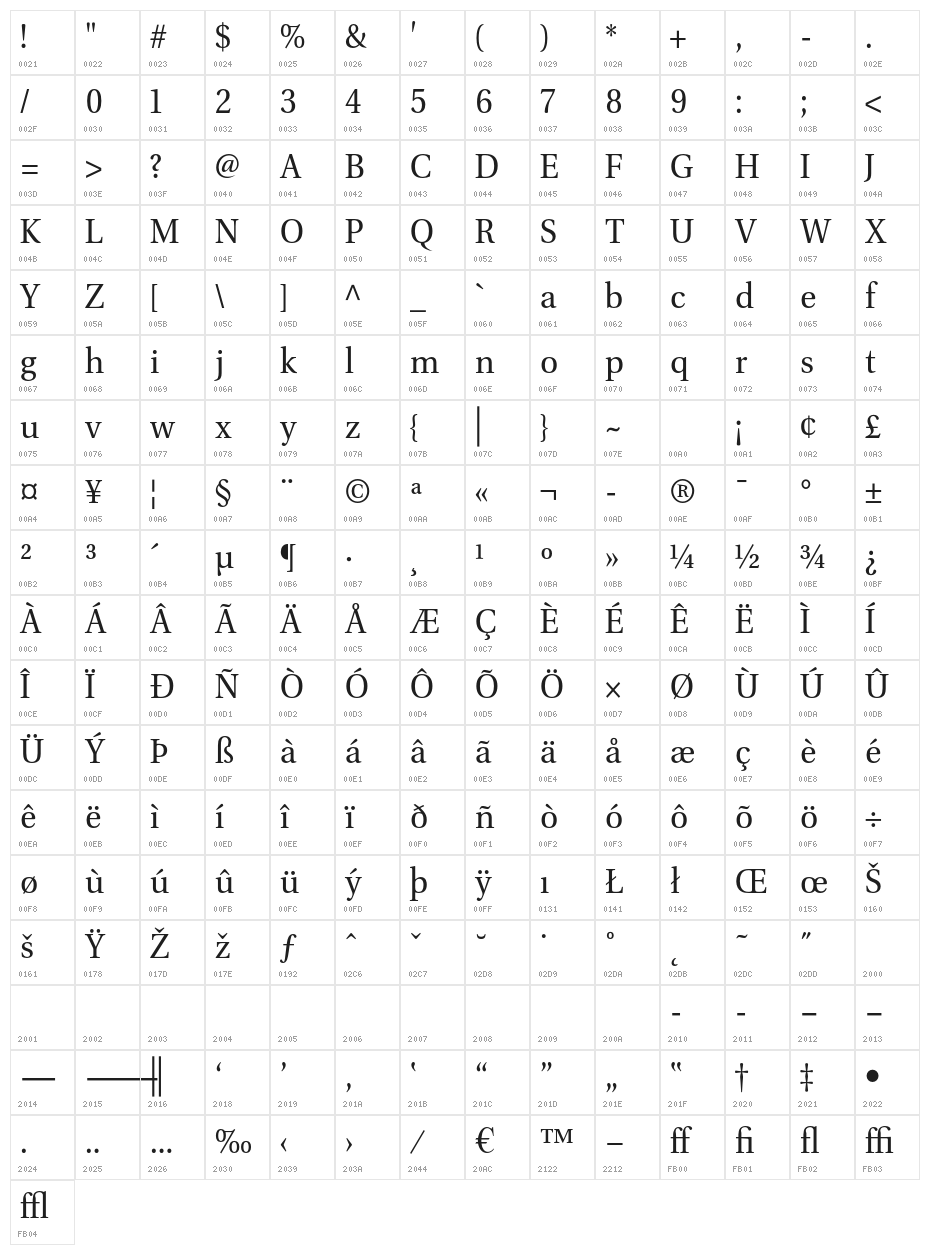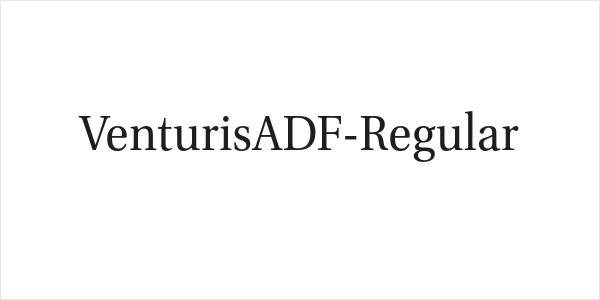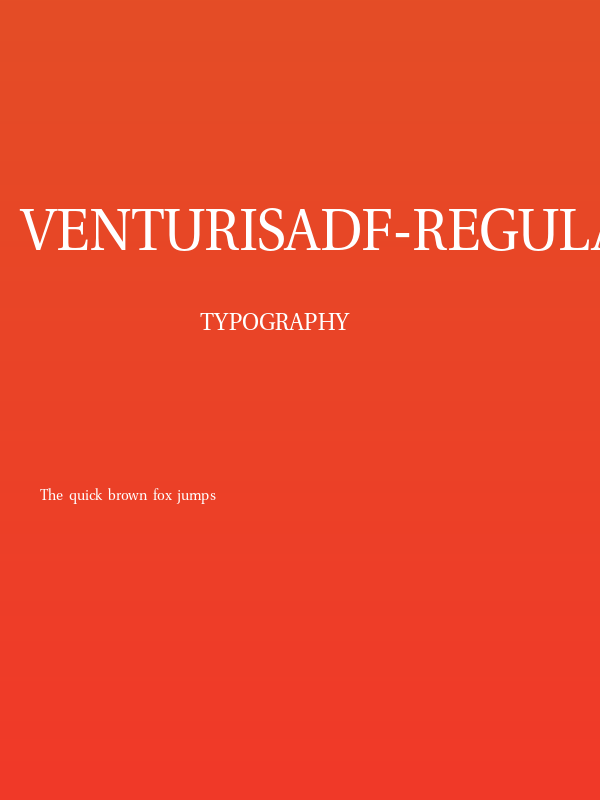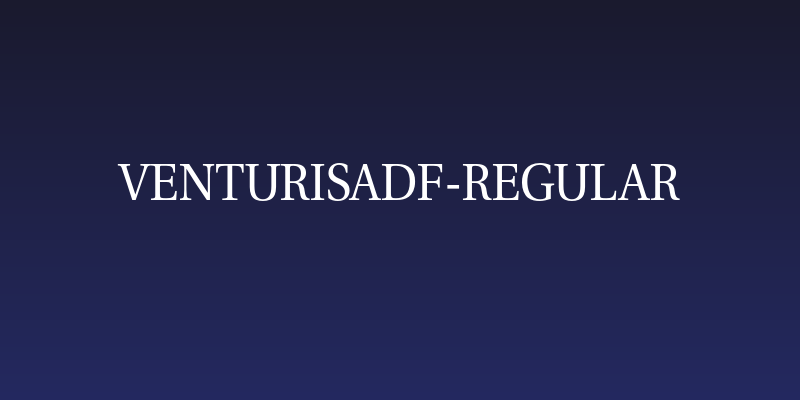
VenturisADF-Regular Font
| Gesamtstil | Classic |
| Anwendungsfall | Headlines, Body text, Logos |
| Vorgeschlagene Projekte | Ideal for editorial design, book covers, formal invitations, and branding projects that require a touch of sophistication. |